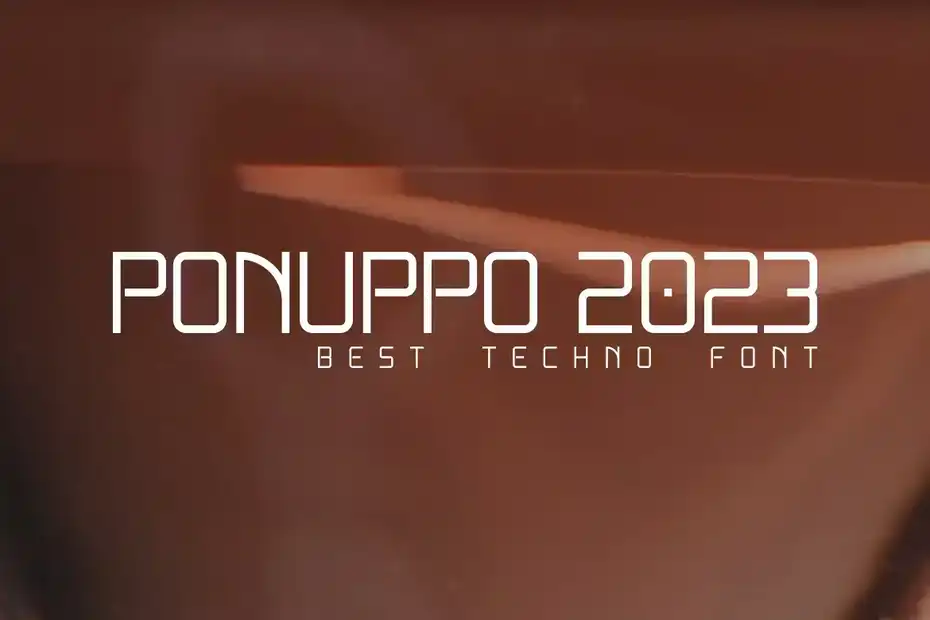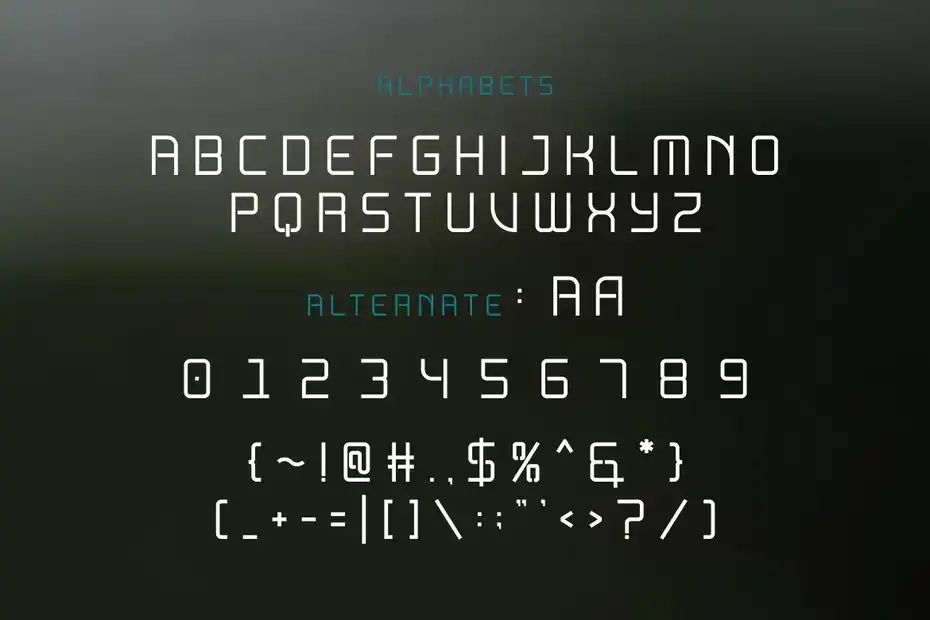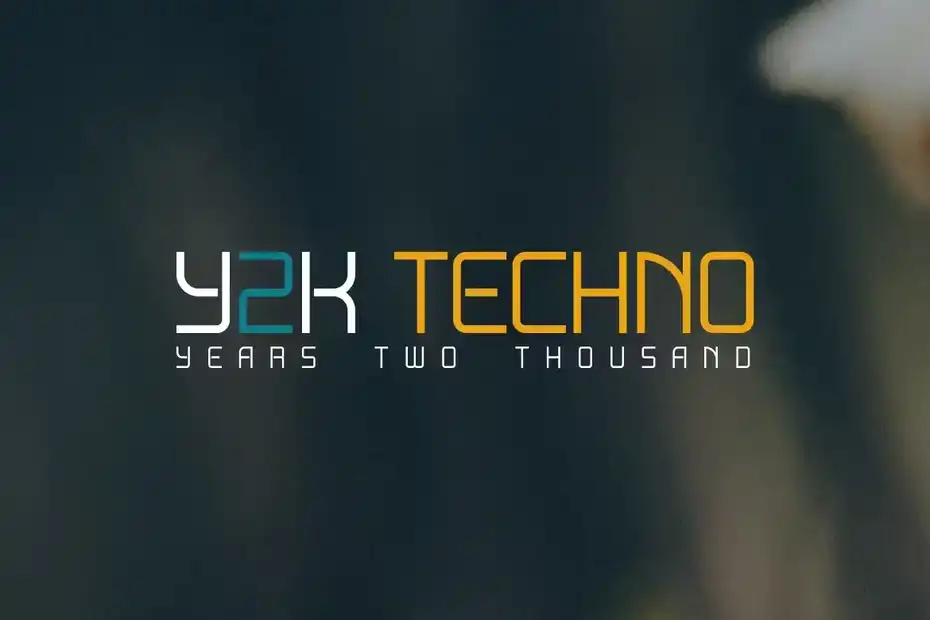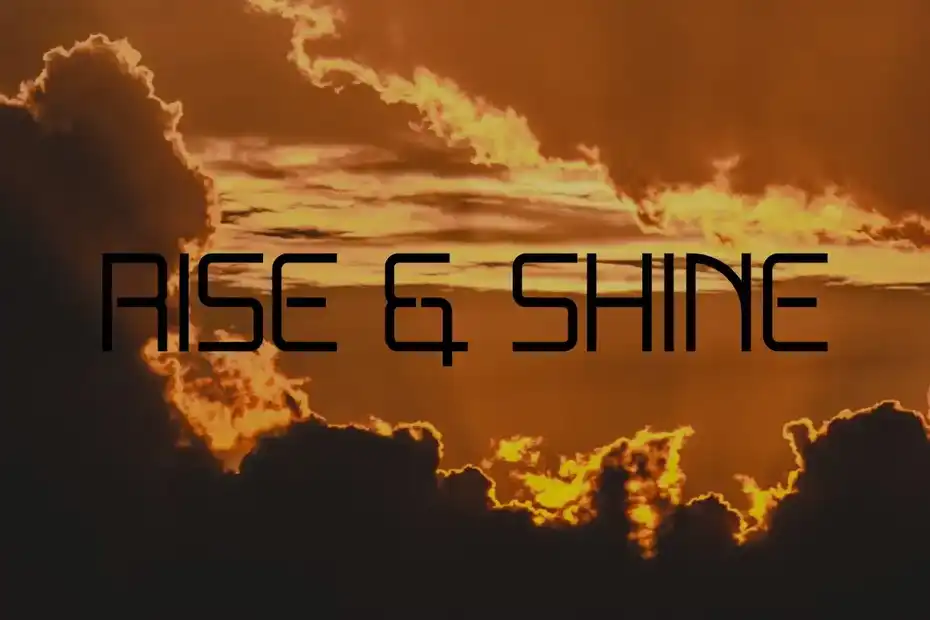
دانلود فونت انگلیسی مدرن Vaqoper Font
فونت انگلیسی مدرن Vaqoper Font : این مجموعه شامل یک فونت انگلیسی مدرن است که برای بازی، کارت ویزیت، ورزشی و غیره مناسب میباشد.
• عنوان مجموعه: Vaqoper Font
فونت انگلیسی مدرن Vaqoper Font - 1
فونت انگلیسی مدرن Vaqoper Font - 3
فونت انگلیسی مدرن Vaqoper Font - 5
فونت انگلیسی مدرن Vaqoper Font - 7